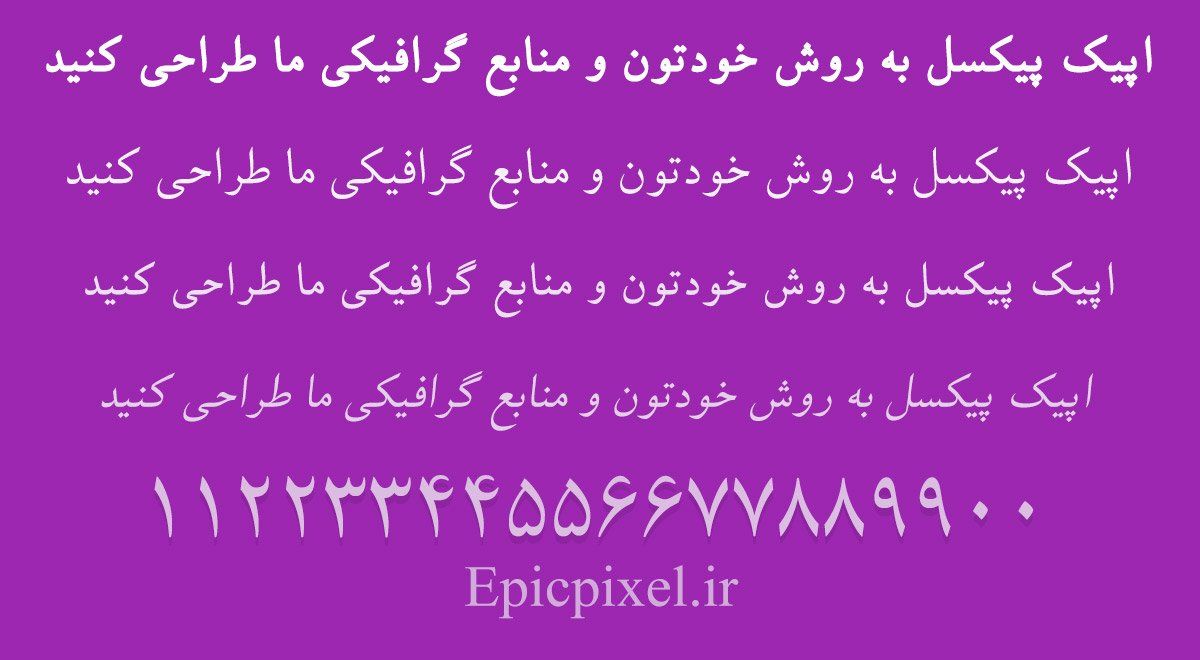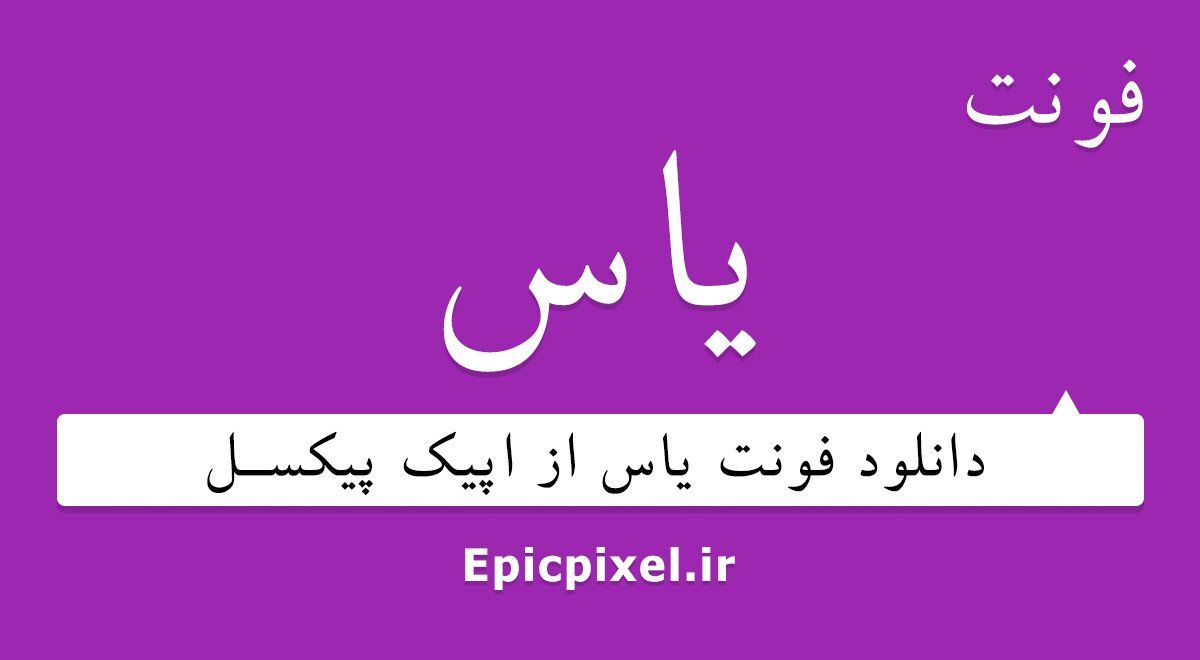
9 فونت یاس فارسی
چرا صفر تو خالی نداره !!!!!
سلام . مدل فونت هست . میتونید از فونت های دیگه استفاده کنید . قبل از دانلود عکس فونت هارو برای مقایسه مشاهده کنید
معمولی ولی کارآمد